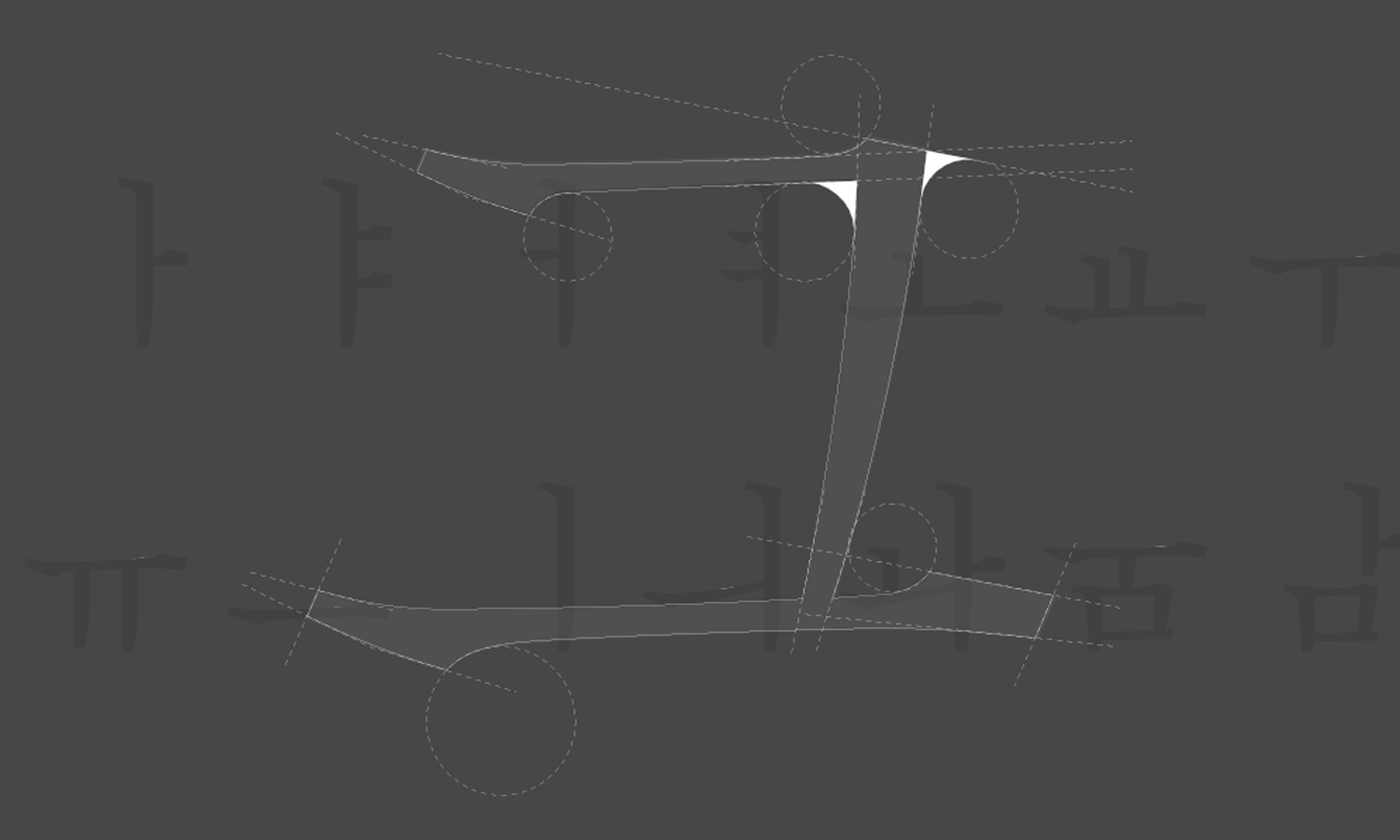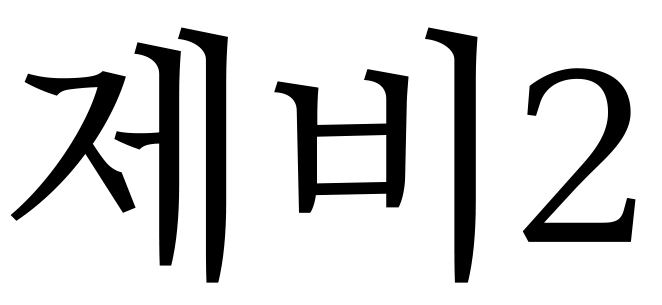
- 산돌 제비2는 기존 산돌 제비의 디테일한 부분들을 수정하여 보다 미려하고 가독성 높은 폰트로 재탄생 시킨 폰트이다.
기존 명조체를 한국적인 곡선과 직선으로 재해석하여 현대적인 스타일을 입힌 본문용 서체로 각진 부리, 기와와 버선코 등 다른 명조들과는 차별화 된 개성을 갖고 있다.